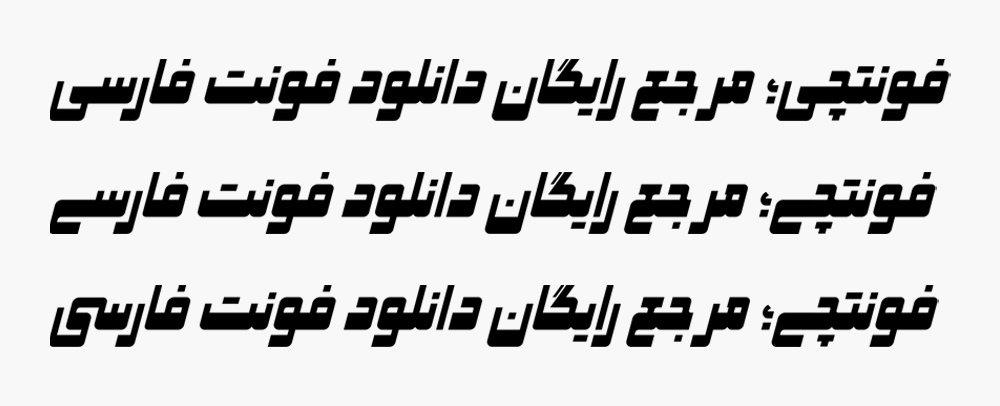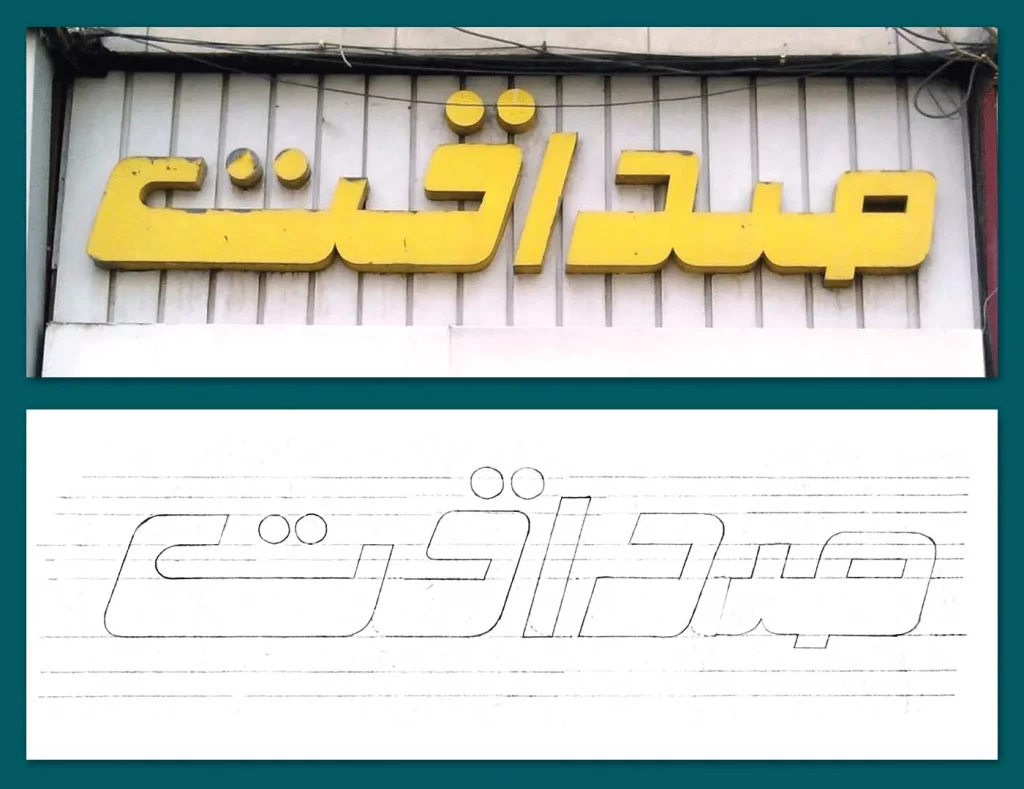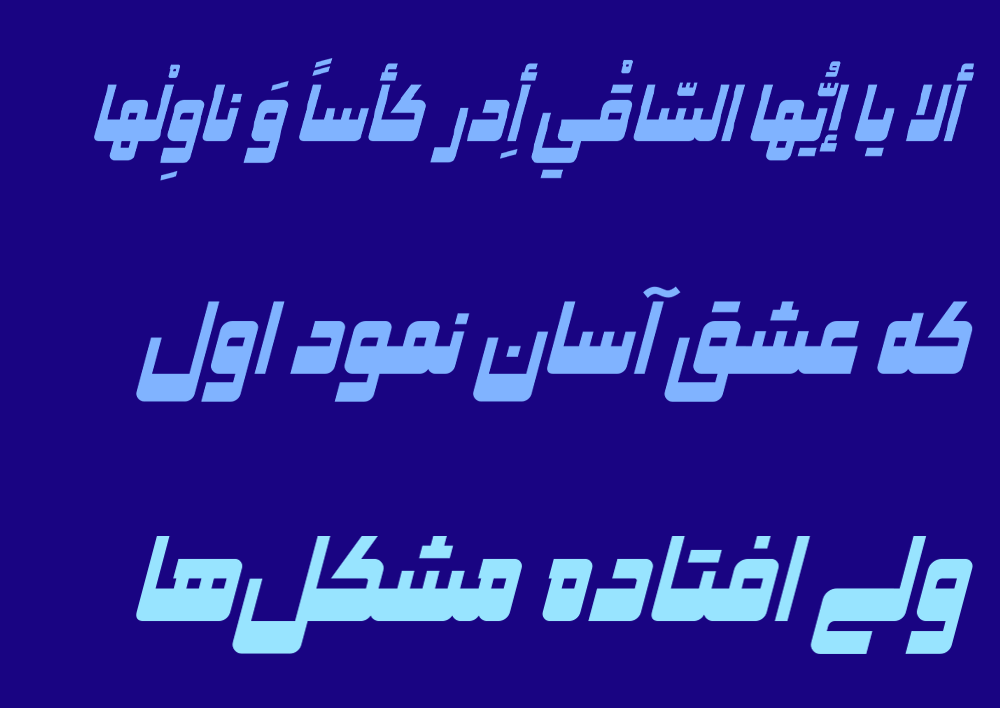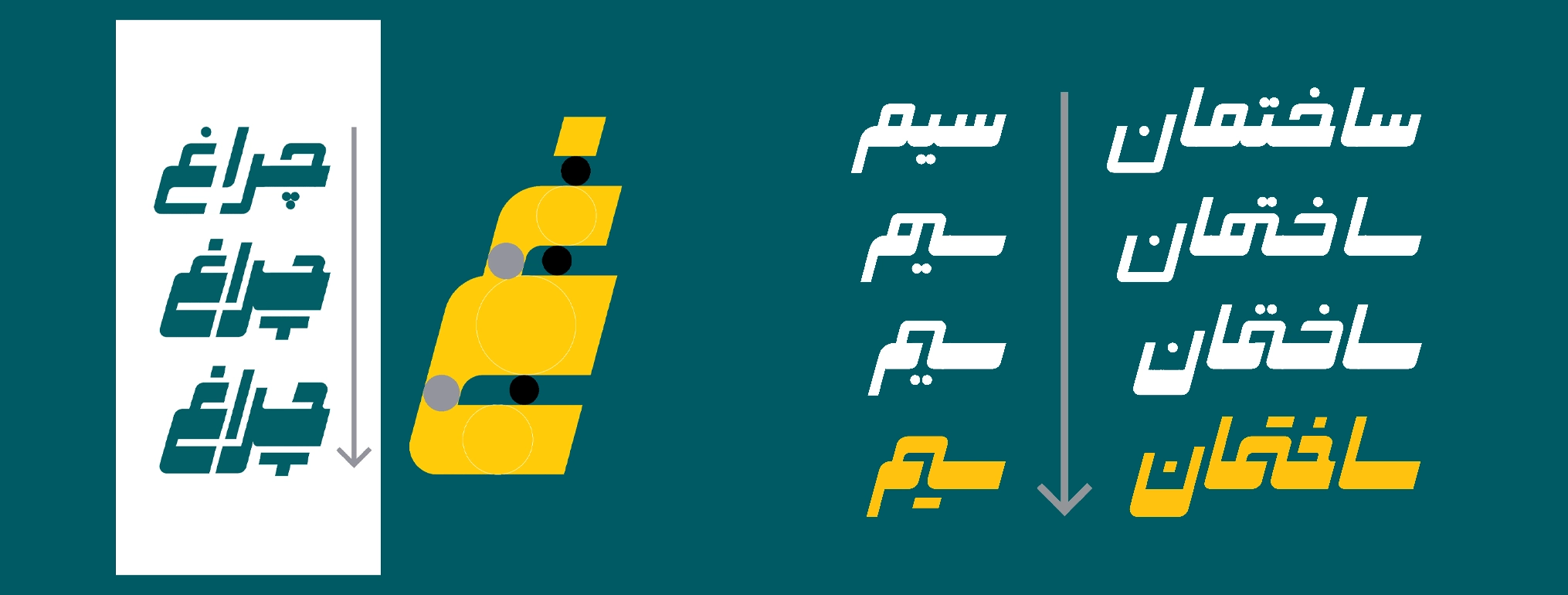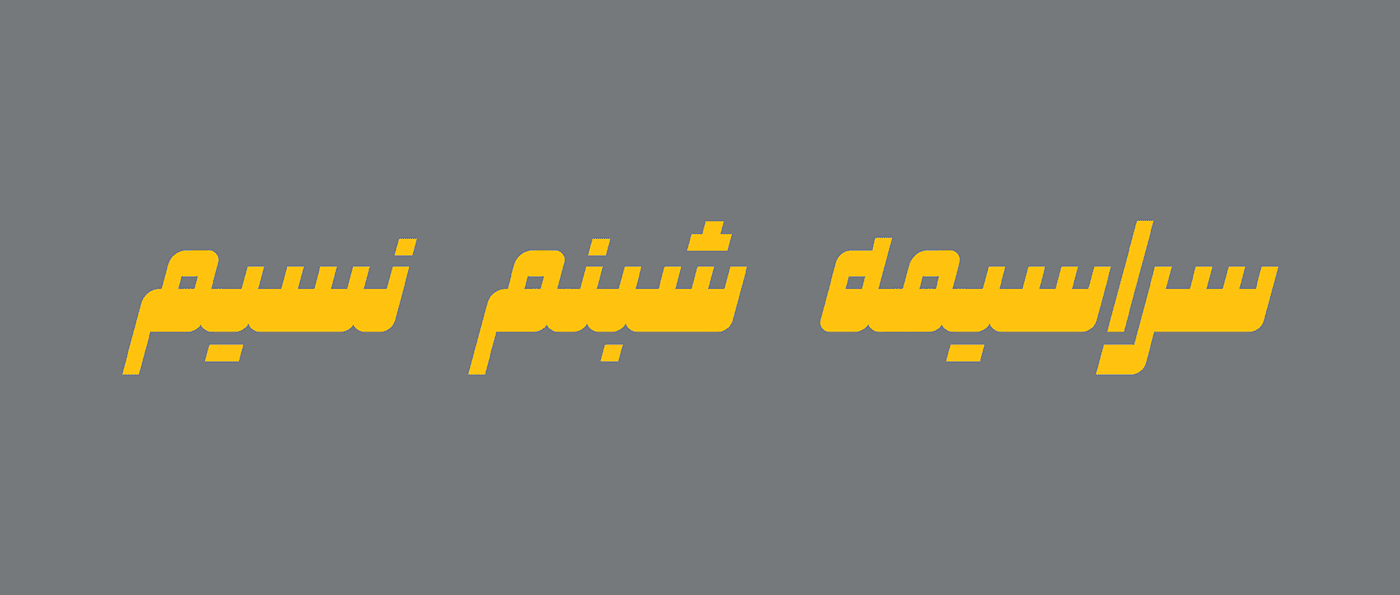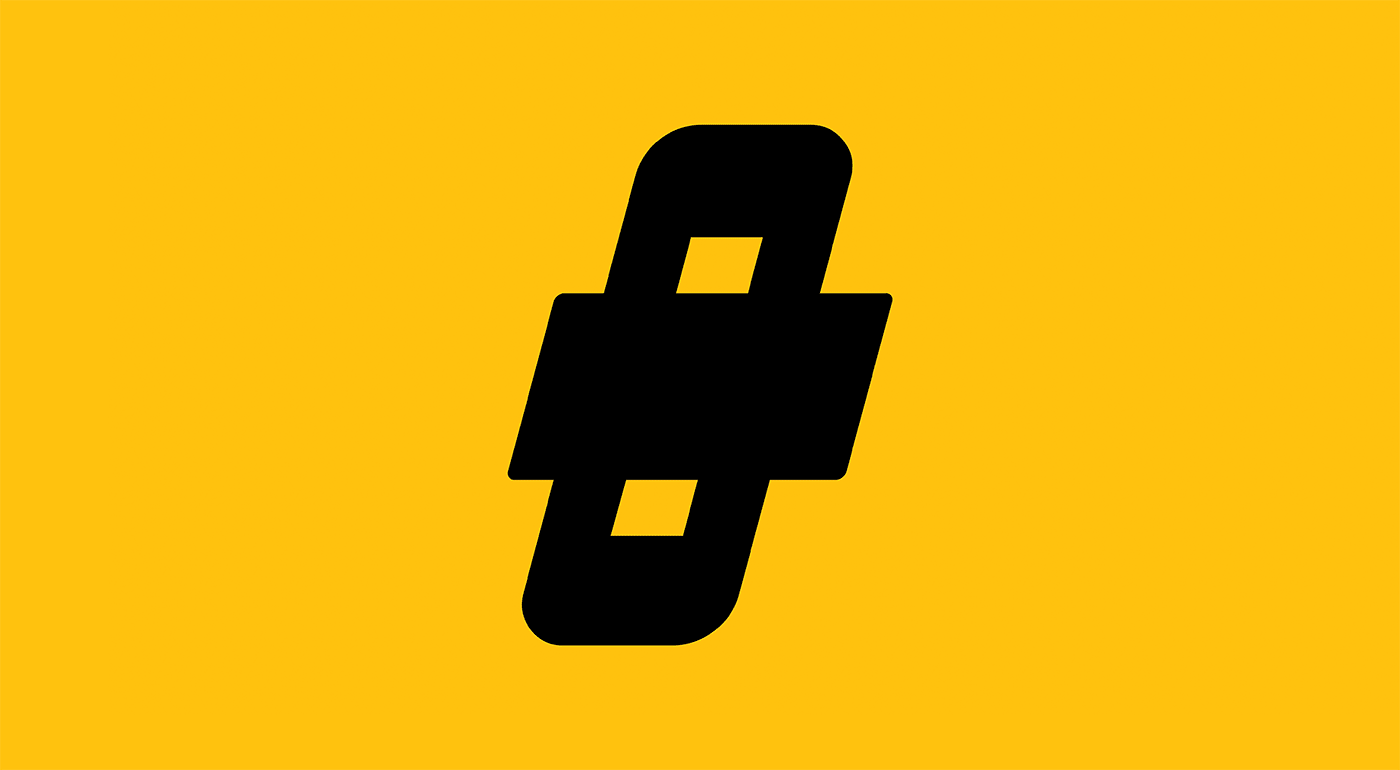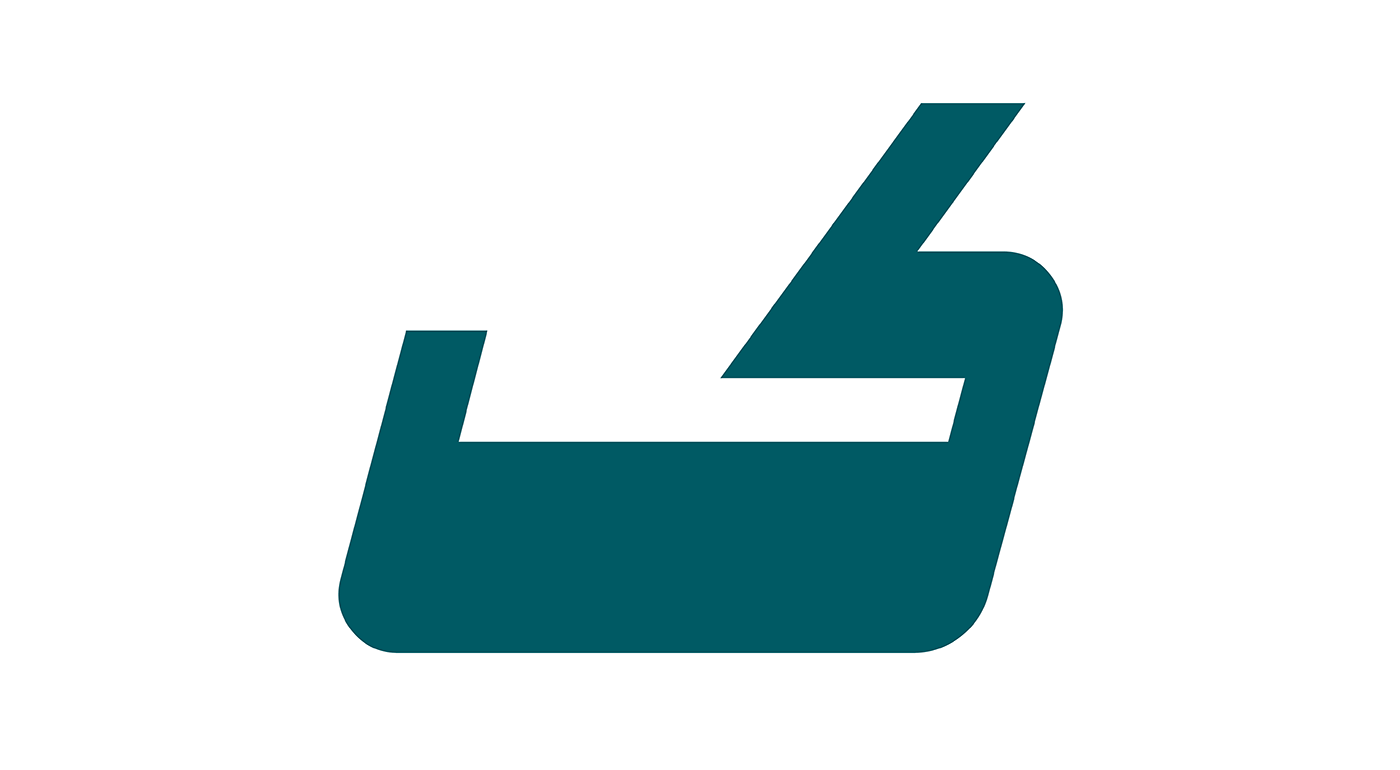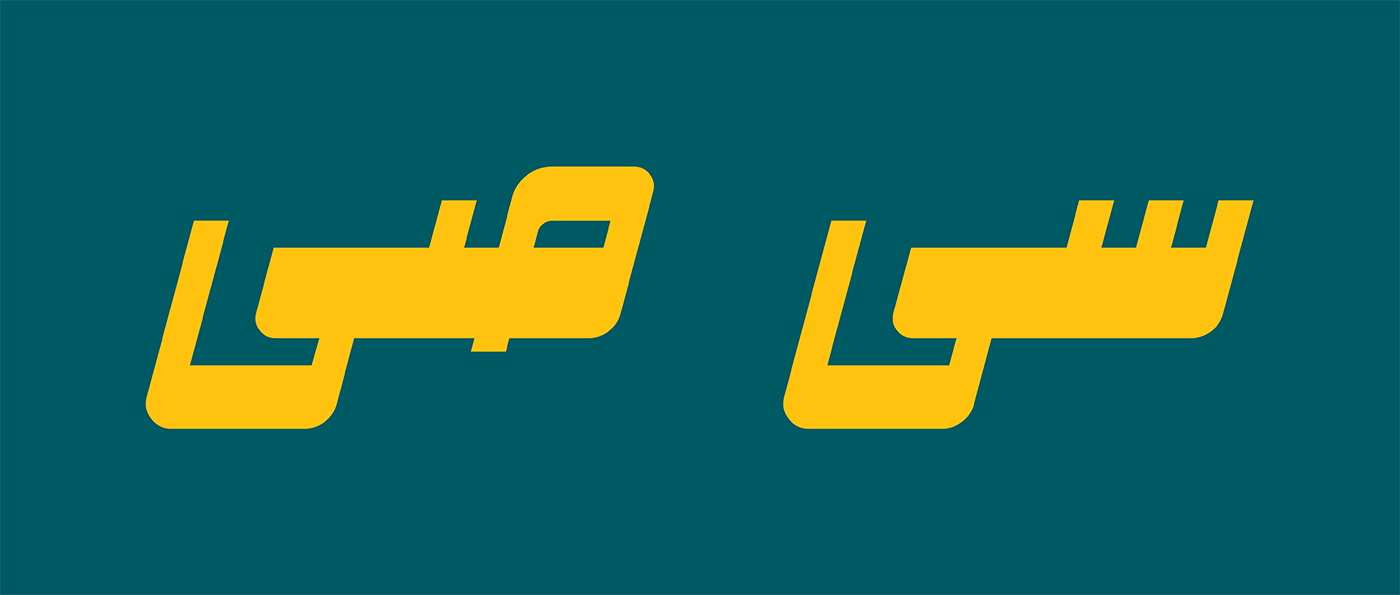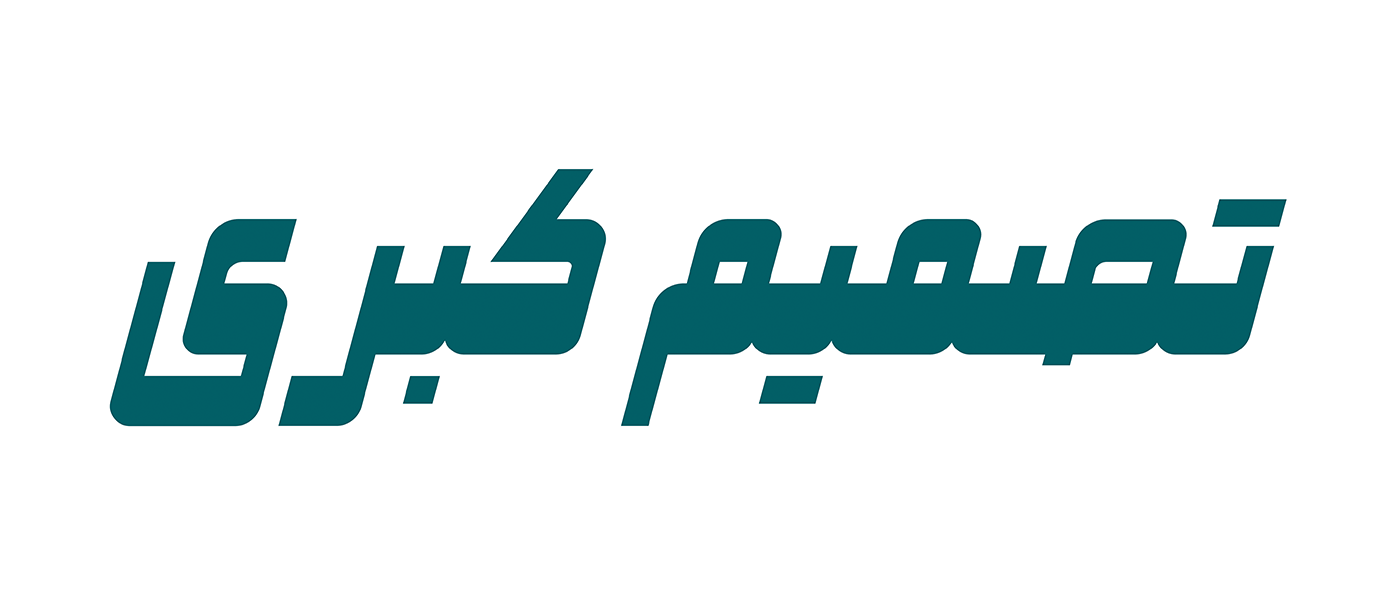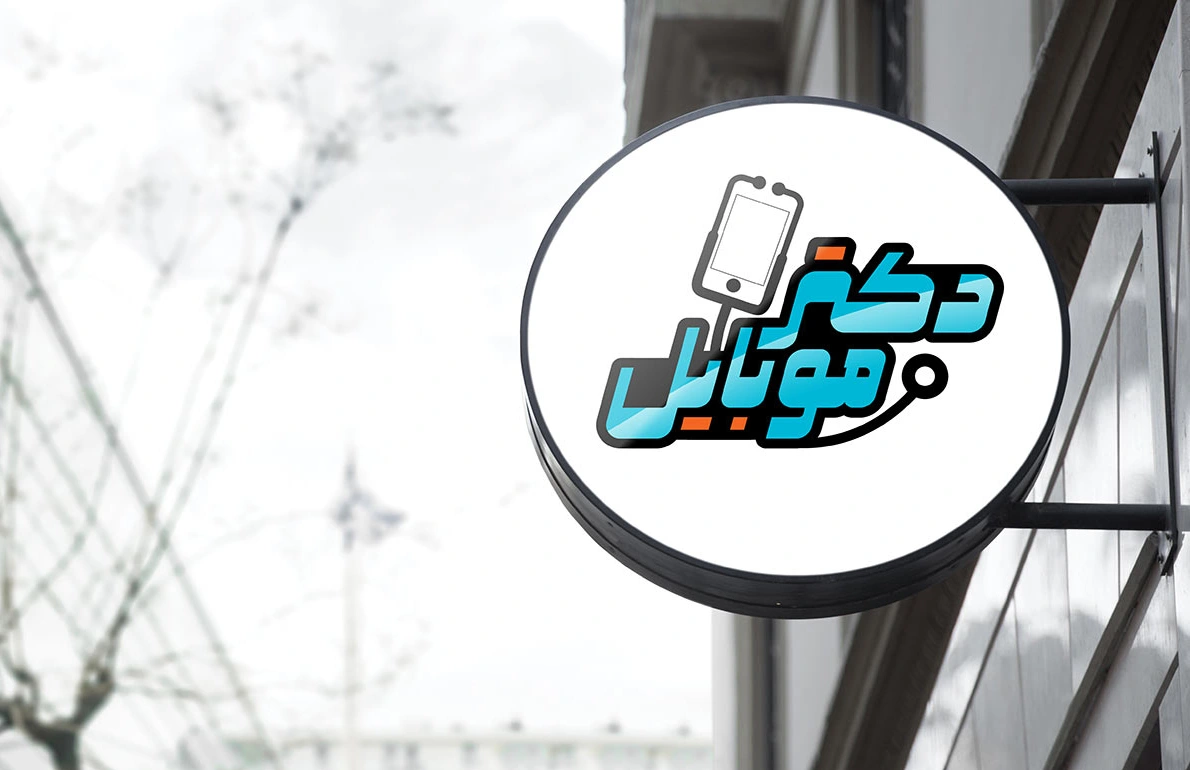
فونت صداقت (Sedaghat)
فونت صداقت (به انگلیسی: Sedaghat) از سری قلمهای مناسب عناوین با ساختاری هندسی است که میتوانید در حوزههای مختلفی همچون تبلیغات، طراحی پوستر، طراحی لوگو تایپ و کارهای گرافیکی نوستالژی از آن استفاده کنید.
قلم صداقت توسط احمد رضا رحیمی پور، با ایده گرفتن از یک تابلوی فروشگاهی با همیننام الهام گرفته شده که ساختار این تابلو نیز همین سبک فونت را داشته است. این طراح با ایده گرفتن از آن سایر حروف را با همین سبک تهیه کرد و در نهایت توسعه نرمافزاری قلم توسط امین عابدی به سرانجام رسید.
در ادامه این نوشته از سایت فونتچی به نقد و بررسی کامل فونت صداقت خواهیم پرداخت؛ فونتی که میتواند برای استفاده در تبلیغات و تابلو سردر فروشگاهها مناسب باشد و در عین حال با فراهم کردن حروف جایگزین متنوعی که دارد، در طراحی نام برند ما برای چنین اهدافی یک ساختار نوستالژیک را بهارمغان آورد.
بررسی و دانلود فونت صداقت (Sedaghat)
فونت صداقت یک تایپ فیس هندسی مورب با زاویه ۱۵ درجه است که دارای لیگیچر (ترکیبات) و حروف جایگزین متعدد است.
ایده اولیه فونت صداقت از یک تابلوی قدیمی حروف برجسته به همین نام گرفته شد و پس از بررسی فرم حروف موجود و طراحی بقیه حروف بر مبنای بیس اصلی، اتودهای اولیه آماده شد؛ سپس با چندین مرحله تغییرات در فرم حروف، زوایا، ضخامتها، سواد، بیاضها و نقطهها تایپ فیسی مدرن با حال و هوای تایپوگرافیهای قدیمی طراحی شد.
احمدرضا رحیمیپور؛ طراح فونت صداقت.
این فونت قابل استفاده در فضای پوستر، طراحی لوگو، طراحی عنوان و تیتر، تابلوسازی و… میباشد.
سبک طراحی و وزن فونت صداقت
قلم صداقت در یک وزن سیاه Black طراحی شده است که همین وزن را پشتیبانی میکند و برای عناوین مناسب است. نقاط در این قلم به صورت در همه حالات چارگوش به صورت چسبان قابل استفاده هستند.
در سراسر خطوط قائم این قلم یک زاویه ۱۵ درجه مورب اعمال شده است و حروف در بخشهای قائم دارای ضخامت کمتر اما در مقابل در بخش افقی دارای ضخامت بیشتری هستند. دندانهها و گردی حروف نیز همین ساختار را حفظ کرده و در منحنیها از بخش بیرونی نیز یک خمیدگی روی مقدار گردی ۱۵ تنظیم شده است.
پشتیبانی از زبان فارسی و عربی
فونت صداقت دو زبانه است و از زبان فارسی و عربی بهصورت مشترک پشتیبانی میکند. رسمخط این دو زبان یکسان بوده و صرفا در برخی حروف و اعداد دارای تفاوتهای جزئی هستند.
بهعنوان مثال در زبان عربی حروفی مثل «ک، ی، ه، ؤ، ئ» و اعداد «۴۵۶» در مقایسه با اعداد فارسی «۴۵۶» دارای تفاوت جزئی هستند که در این قلم همه این موارد پیادهسازی شده است تا ساختاری استاندارد و بین المللی داشته باشد.
دارای حروف جایگزین بسیار متنوع
مهمترین ویژگی فونت صداقت پشتیبانی از ترکیبات و حروف جایگزین بسیار متنوع است که امکان تایپ عبارات و جملات را در چند حالت مختلف به شما خواهد داد. چنین ویژگی باعث کمک به خوانایی بهتر متن، جلب توجه بیشتر کاربر روی کلمات کلیدی مهم همچون نام برند و کمک به کاربر در جهت اصلاح خوانایی، در کنار زیباتر و نمایشیتر شدن قلم خواهد شد.
در فونت صداقت برای رسیدن به این حالات مختلف حروفی مانند «ح، ع» لبهدار و «ک، ب، ف» کشیده یا لبهدار و همچنین استفاده از ترکیبهای جدید مانند اتصال دندانه افراشته «ص، س، ب، ن، ی» به حروف «ر، ن، م،ی» باید از ترکیب شیفت و همزه برای انتهای کلمه یا حروف جدا و از همزه برای بین حروف استفاده کنید.
در تصاویر زیر نمونهای از این ترکیبات و حروف را برای حالات مختلف ذکر شده در بالا مشاهده میکنید که با کنار هم قرار دادن هر یک از این ترکیبات میتوان در یک جمله از همه حالات مختلف یا یک حالت خاص برای کلمهای خاص استفاده کرد.
مناسب طراحی لوگو تایپ و پوستر
ویژگی دیگر قلم صداقت امکان استفاده از آن برای طراحی لوگو تایپ به لطف ساختار هندسی و در کنارش پشتیبانی از حروف و ترکیبات جایگزین است. این ترکیبات در طراحی لوگو به شما امکان ساخت نام برند شما را بر اساس چند حالت مختلف خواهد داد.